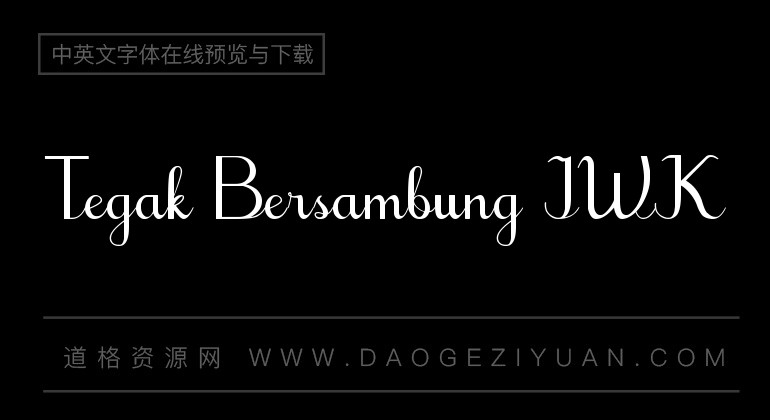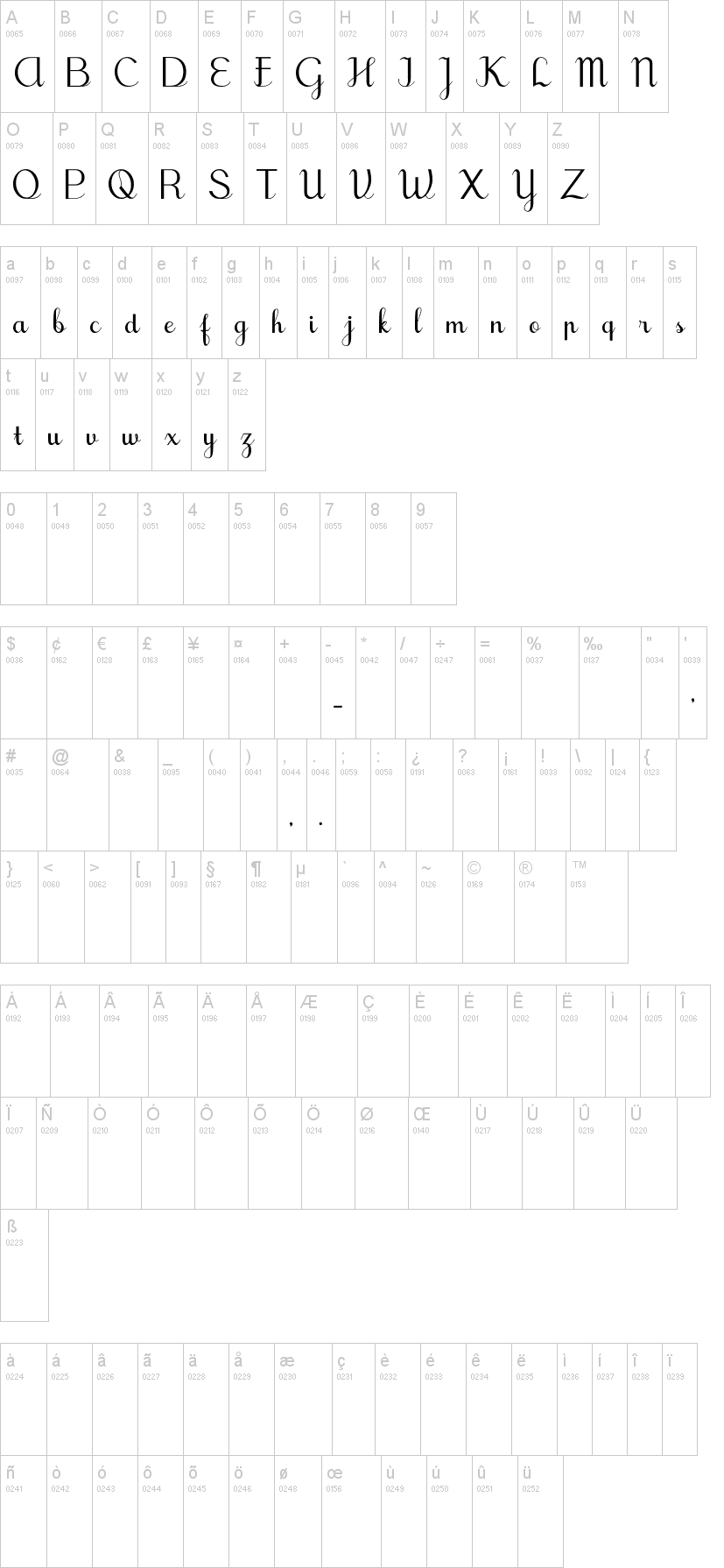
Tegak Bersambung IWK字体是一种印尼文字体,由印尼设计师Irwan Widyanto Kurniawan设计,该字体可以用于商业及其他用途。Tegak Bersambung IWK字体的特点是它的笔画宽度比较宽,更易于识别,而且字体的粗细也比较明显,使得文字更加美观大方。此外,Tegak Bersambung IWK字体还具有良好的可读性,可以帮助读者更容易理解文字的意思。内容介绍
Tegak Bersambung IWK是一款非常不错的手写艺术字体,具有很好的视觉感,适合于文化类的宣传设计、商业类品牌的广告和产品包装设计以及个性化文字排版等较多场景。